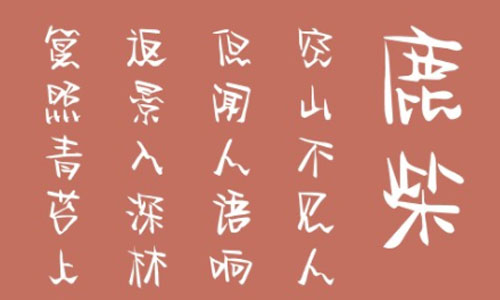
倉耳再見那些年體字體具有較強的書法風格,筆畫粗細變化明顯,字體底部添加小尾巴作為裝飾,結(jié)構(gòu)緊湊,外柔內(nèi)剛,遒勁有力。字體對傳統(tǒng)的書法字體進行改造,設(shè)計了專門的筆形并且添加波浪形的筆形進行裝飾,外柔內(nèi)剛,柔韌有力,彰顯青春張揚的個性,歡迎大家前來下載使用。